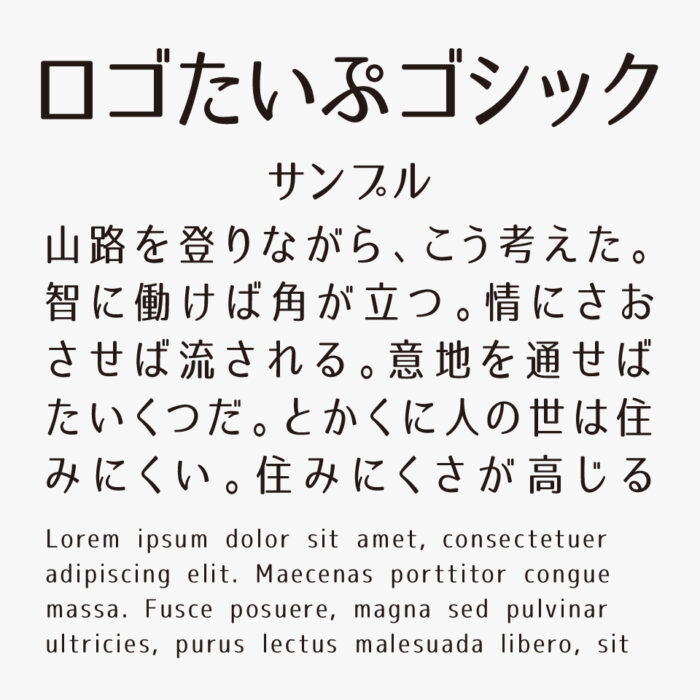
ロゴたいぷゴシック(コンデンスド)
ロゴたいぷゴシック(コンデンスド)フォントは、「ロゴたいぷゴシック」にコンデンスド(長体)の加工を施したフォントになります。ロゴデザインやタイトルロゴ、見出しなどに向いている漢字も含まれる日本語フリーフォントになります。
長体フォントなので、少しスタイリッシュでかっこいい印象になり、ロゴやタイトルデザインに使うとスマートでクールな印象になります。かつ、どことなく優しくエレガントな柔らかいデザインも特徴の1つです。
収録文字は、数字、アルファベット、記号、かな文字(ひらがな・かたかな)、教育漢字、常用漢字、第一水準漢字、第二水準漢字(途中まで完成)、その他主要な多言語が収録されています。